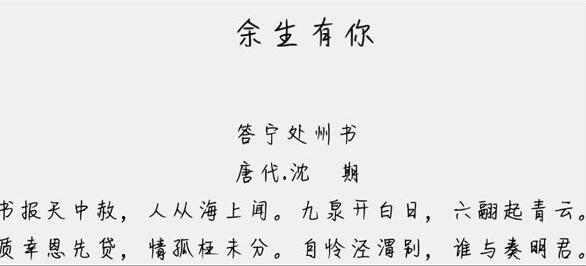
余生有你是一款十分好用,且非常漂亮的中文字體,同時(shí)也是由文道字庫(kù)傾情發(fā)布的作品,字體的角度、大小、距離都設(shè)計(jì)得非常恰,筆畫婉轉(zhuǎn)清麗,適應(yīng)于報(bào)紙和雜志和書籍中常用字體海報(bào)、個(gè)性促進(jìn)品牌標(biāo)志設(shè)計(jì)、文本裝潢、信息展示、篆刻制模英文、數(shù)據(jù)制作、裝潢設(shè)計(jì)、視覺(jué)設(shè)計(jì)、字帖等一切合法應(yīng)用場(chǎng)景,有喜歡的朋友可免費(fèi)下載收藏。